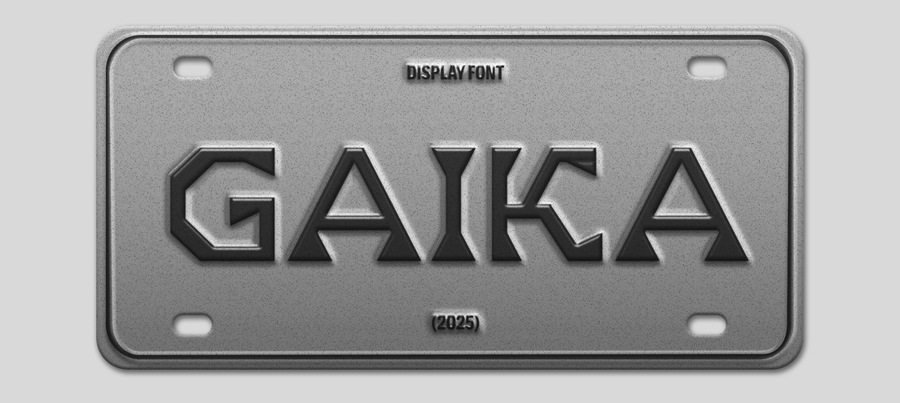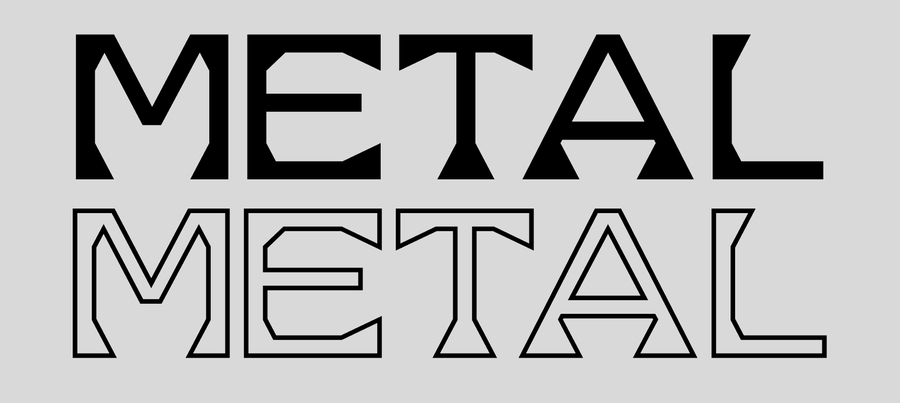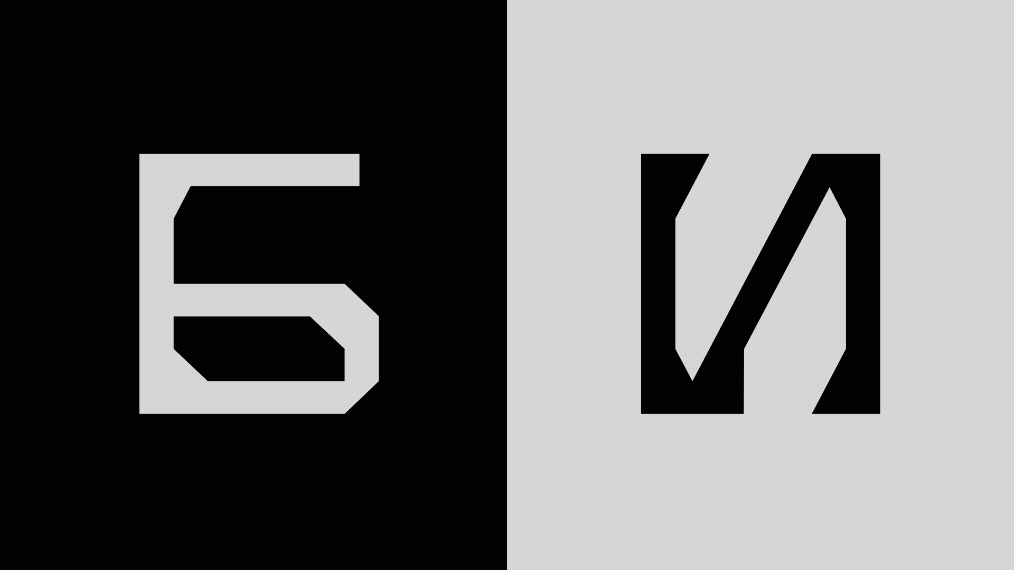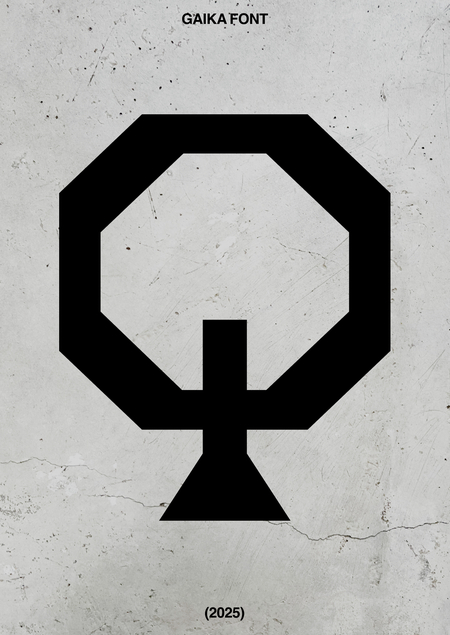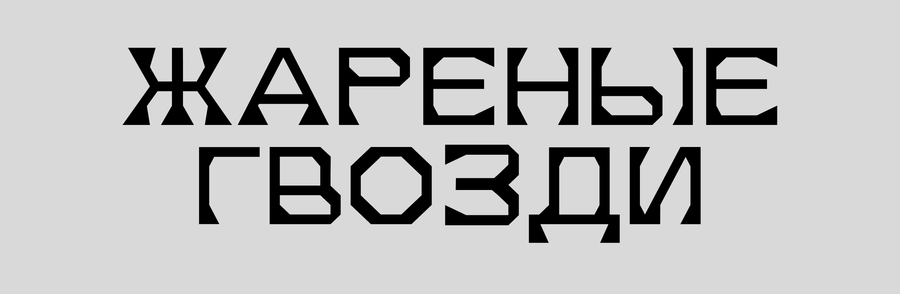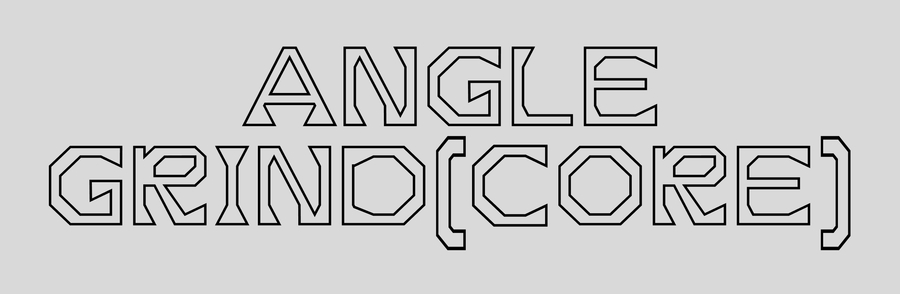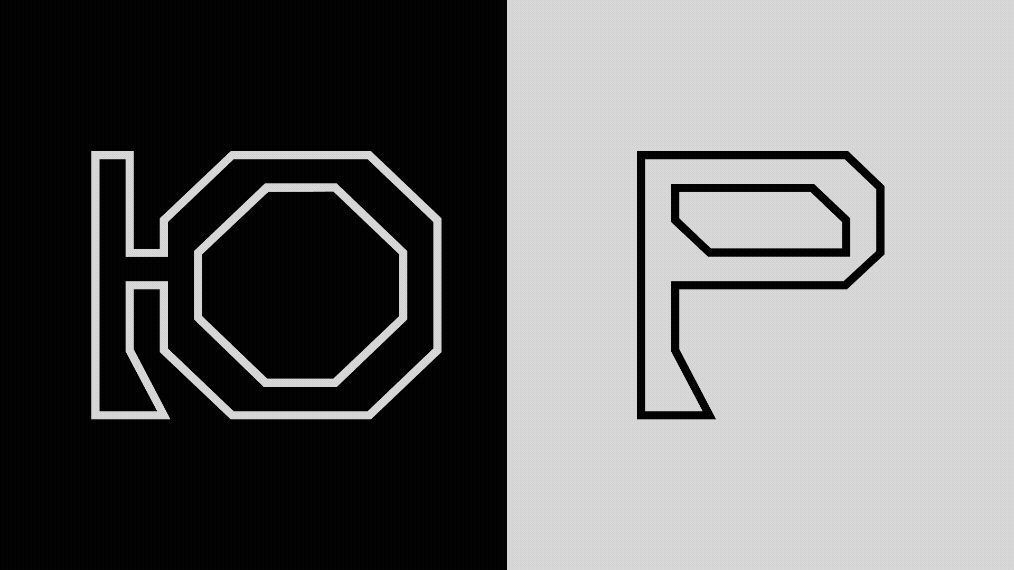
GAIKA FONT — акцидентный шрифт, вдохновлённый брутализмом, технической эстетикой и формой гаек. Угловатые очертания и характерные скосы создают индустриальный ритм.
Шрифт имеет два начертания: Regular и Stroke, предназначен в первую очередь для заголовков и крупного текста.